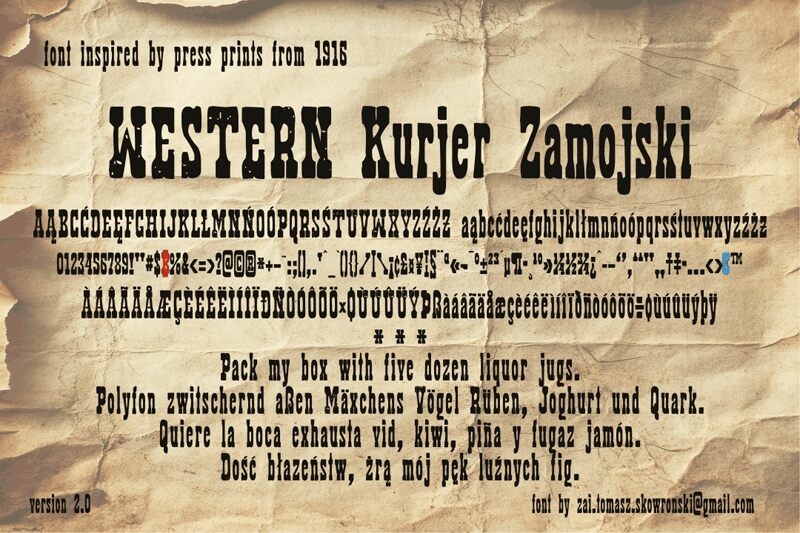
zai Western Kurjer Zamojski
Zai Western Kurjer Zamojski ist eine kostenlose Western-Display-Schrift mit der Attitüde alter Saloon-Schilder, die jedoch in seltsamere, theatralischere Formen übersetzt wurde. Die Buchstaben wirken zugleich geschnitzt und aufgequollen; die Mischung aus hohen, schmalen Formen, stumpfen slab-artigen Abschlüssen und tiefen Rundungen verleiht der Schrift eine raue Atmosphäre wie von alten Western-Plakaten, statt eines sauberen Vintage-Looks.
Sie eignet sich hervorragend für Poster-Schlagzeilen, Whiskey-Etiketten, Veranstaltungsflyer, Spiel-Titelbildschirme und Buchcover, bei denen eine kostenlose Schrift mit einem staubigen, erzählerischen Charakter gefragt ist. Da die Formen sehr stilisiert und unregelmäßig sind, funktioniert sie am besten in kurzen Wörtern, Logos und Titelkarten, bei denen die eigenwilligen Western-Silhouetten ihre Wirkung voll entfalten können.